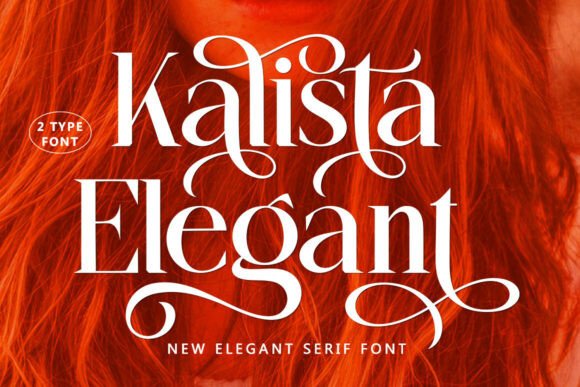
Kalista Elegant
หากคุณกำลังมองหาเนื้อหาคุณภาพสูงเช่น Kalista Elegant แพ็คเกจพรีเมียมนี้เป็นตัวเลือกที่ยอดเยี่ยมสำหรับโปรเจ็กต์สร้างสรรค์ของคุณ
สร้างขึ้นอย่างแม่นยำ Kalista Elegant ให้เวกเตอร์ที่สะอาด พิมพ์ตัวอักษรที่ราบรื่น และใบอนุญาตเชิงพาณิชย์เพื่อความสบายใจ
ไม่ว่าคุณจะสร้างผลิตภัณฑ์ POD (Print on Demand) คำเชิญงานแต่งงาน หรือกราฟิกโซเชียลมีเดีย Kalista Elegant ก็เหมาะสมอย่างยิ่ง